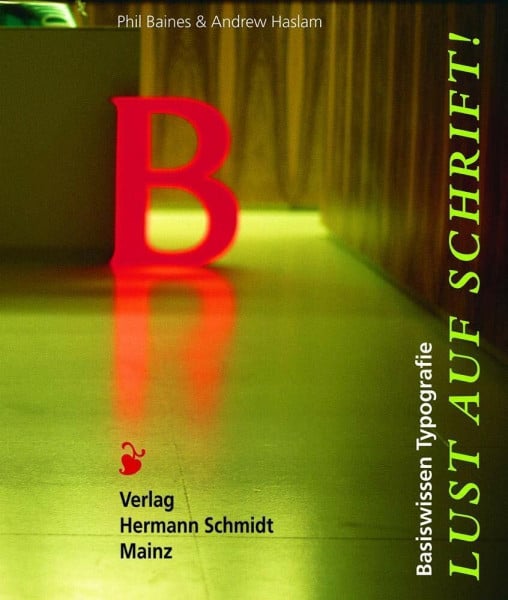
Lust auf Schrift!.Basiswissen Typografie
Als Phil Baines in den Achtzigern selbst Grafikdesign studierte, vermisste er den großen Bogen von der Sprache als gesprochenem System über Form und Funktion von Schrift und Gestaltung, Schriftklassifizierung und -entwurf, Geschichte und Gegenwart, Gestaltung und Herstellung – eben einen umfassenden Grundlagenkurs. Wir wissen nicht, ob er sich geschworen hat „Meinen Studenten soll es mal besser gehen“, aber gemeinsam mit Andrew Haslam gelingt ihm ein Rundumschlag, auf den Ein- und Aufsteiger ihre Grafikdesign-Karrieren bauen können. Ein idealer Einstieg in die Welt von type & typography. Ein Buch der Antworten auf die vielen Fragen, die Baines und Haslam in ihrer langen Lehr-Erfahrung gestellt bekommen haben. Ein Buch, in das die Erfahrung der erfolgreichen und stilprägenden Kreativleistung der beiden renommierten Gestalter einfließt. Und das Lust macht auf Schrift – und auf den gekonnten Umgang damit…